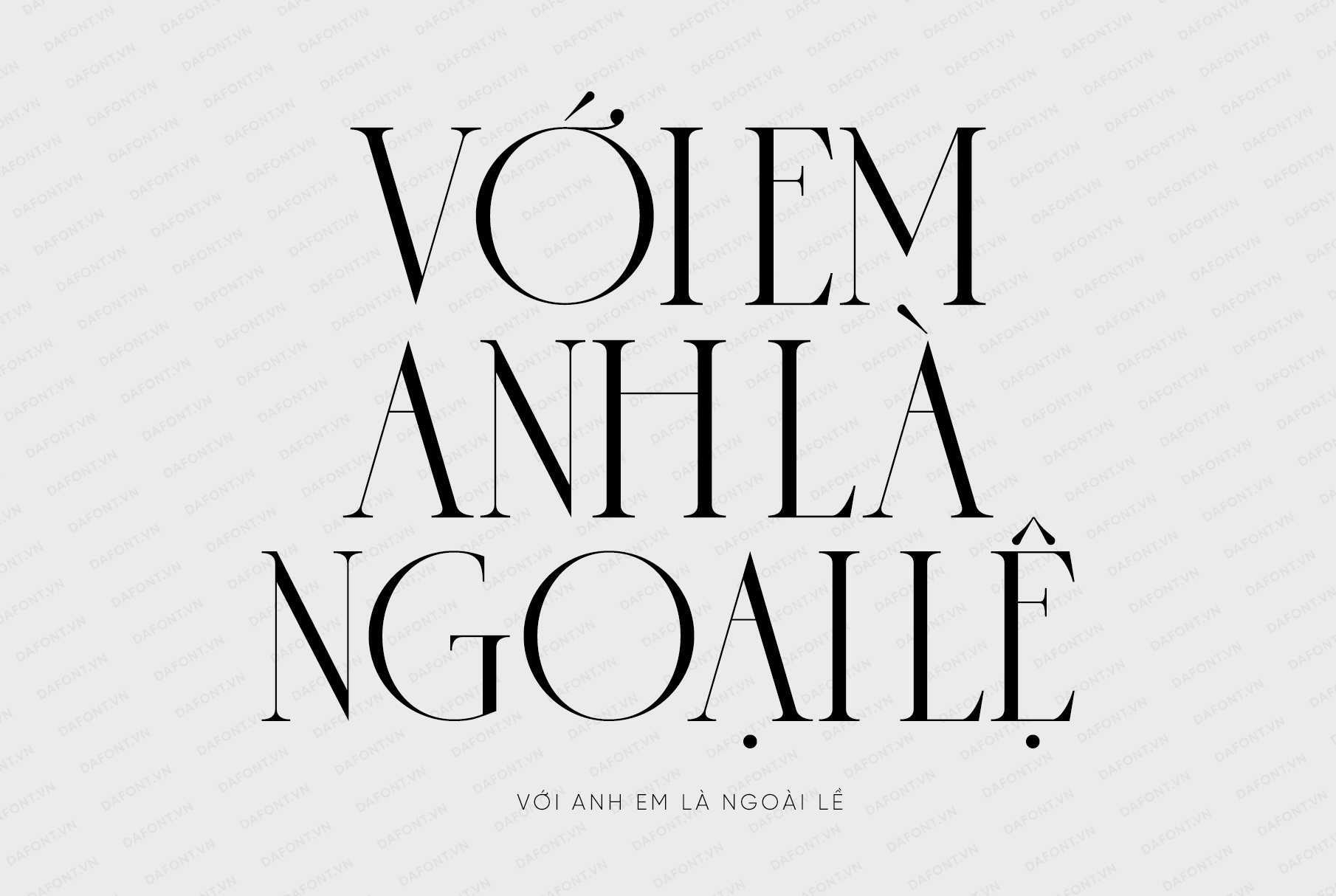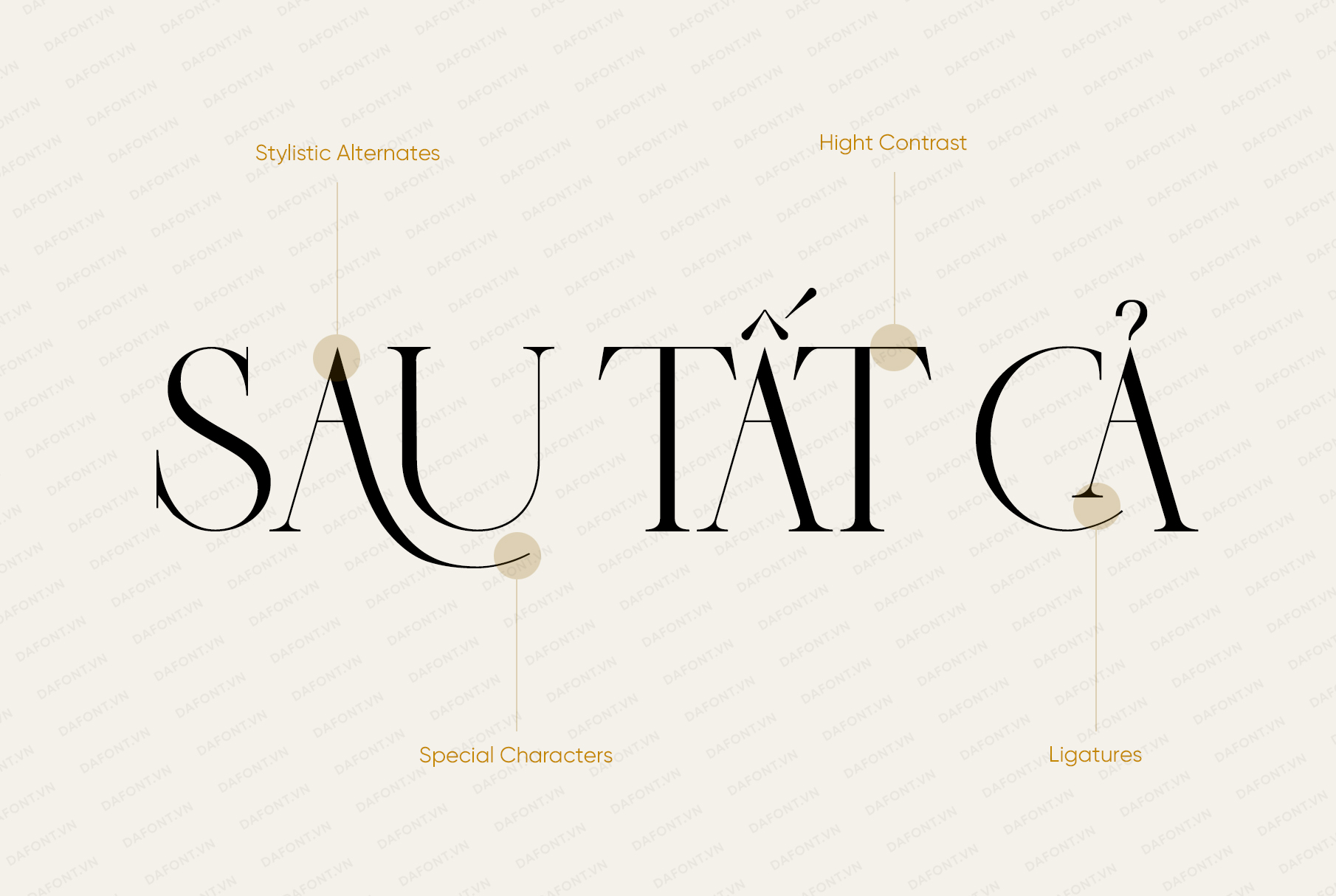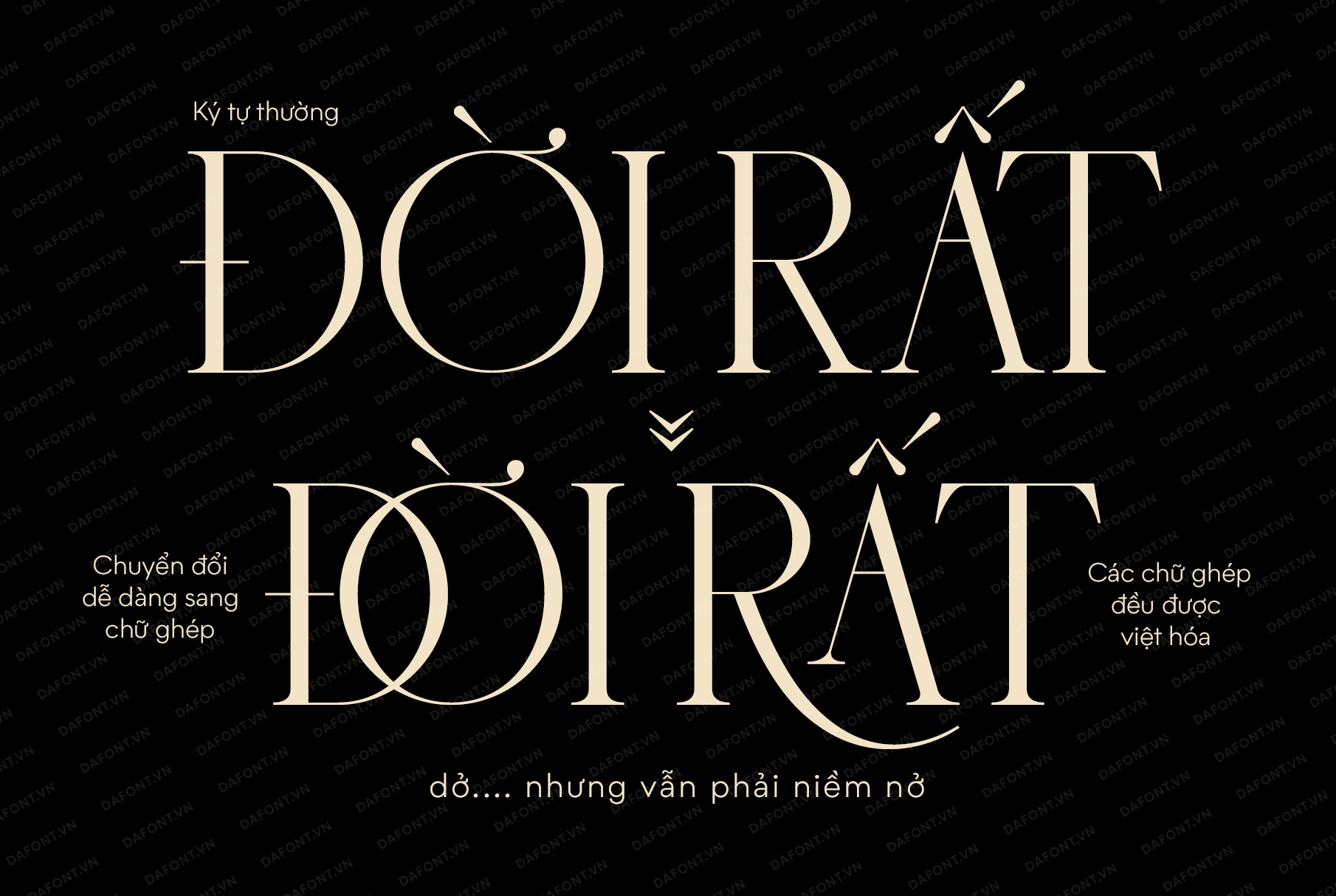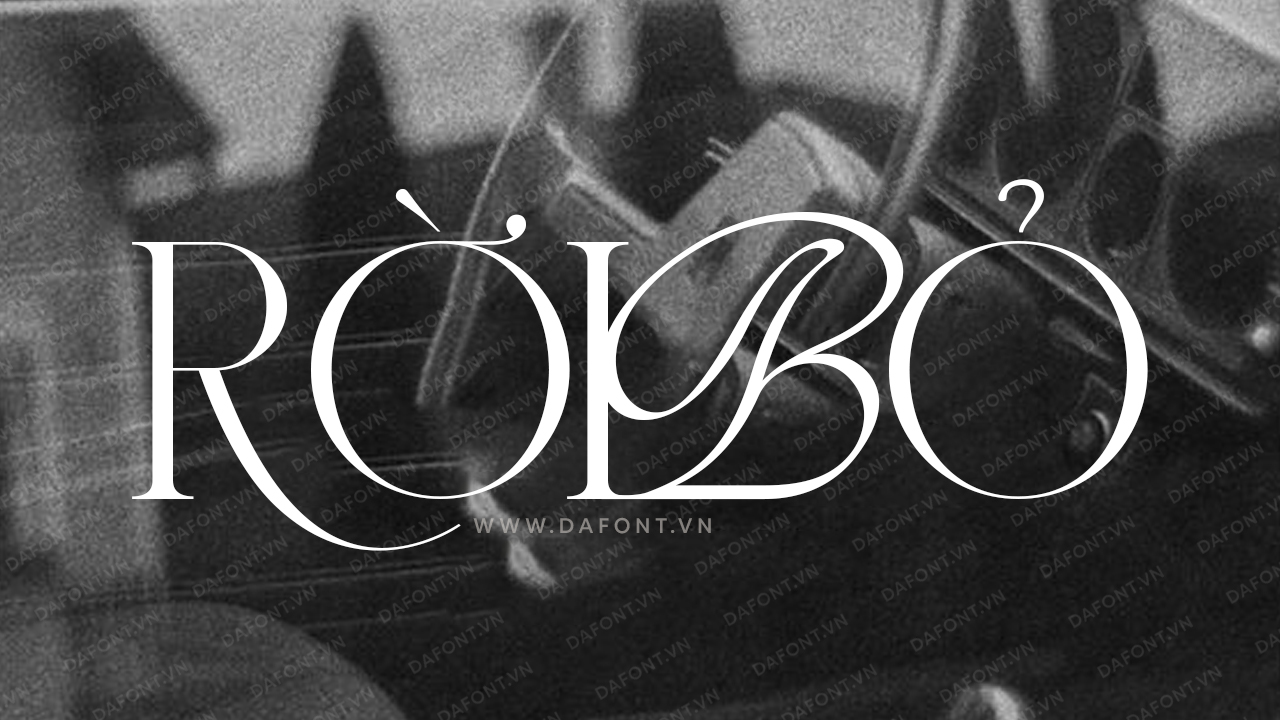
Trong thế giới thiết kế, font chữ không chỉ đơn thuần là phương tiện truyền đạt thông tin mà còn là yếu tố quan trọng tạo nên phong cách và bản sắc riêng cho mỗi tác phẩm. Font việt hóa DFVN Sauvage là một trong những ví dụ điển hình về sự kết hợp hoàn hảo giữa tính thẩm mỹ và tính ứng dụng cao.
Sauvage kiểu chữ có chân (serif) tinh tế, lấy cảm hứng từ phong cách Art Deco. Mang đậm nét thanh lịch, hiện đại và sáng tạo, phù hợp cho nhiều thiết kế khác nhau từ in ấn đến kỹ thuật số.
Phong cách hiện đại
Sauvage được thiết kế với đường nét tinh tế, mềm mại nhưng vẫn giữ được sự mạnh mẽ và rõ ràng. Các ký tự trong Sauvage có độ cân đối cao, tỷ lệ hoàn hảo giữa các phần của chữ, tạo nên sự hài hào và đẹp mắt. Font chữ này mang lại sự hiện đại, thanh lịch và sang trọng, phù hợp với các dự án thiết kế đòi hỏi tính thẩm mỹ cao như thiết kế logo, thiệp mời, tạp chí, bao bì, thời trang, xây dựng thương hiệu…
Ký tự thay thế và chữ ghép
Sự lựa chọn đa dạng về ký tự thay thế và chữ ghép làm cho Sauvage trở nên cực kỳ linh hoạt. Mỗi ký tự trong Sauvage đều được chăm chút kỹ lưỡng, đảm bảo tính thẩm mỹ cao và dễ đọc. Các góc bo tròn và các đường nét uốn cong mềm mại cùng với các nét nối thanh mảnh tạo nên sự liên kết hài hòa giữa các ký tự.
DFVN Sauvage là kiểu font hiển thị phù hợp sử dụng cho tiêu đề, nó sẽ nổi bật khi được sử dụng ở kích thước lớn. Ngoài ra, với hơn 500 glyph bao gồm các chữ cái thay thế và chữ ghép cực đẹp đều được việt hóa cẩn thận và dễ dàng chuyển đổi qua lại giữa các ký tự bằng tính năng OpenType.